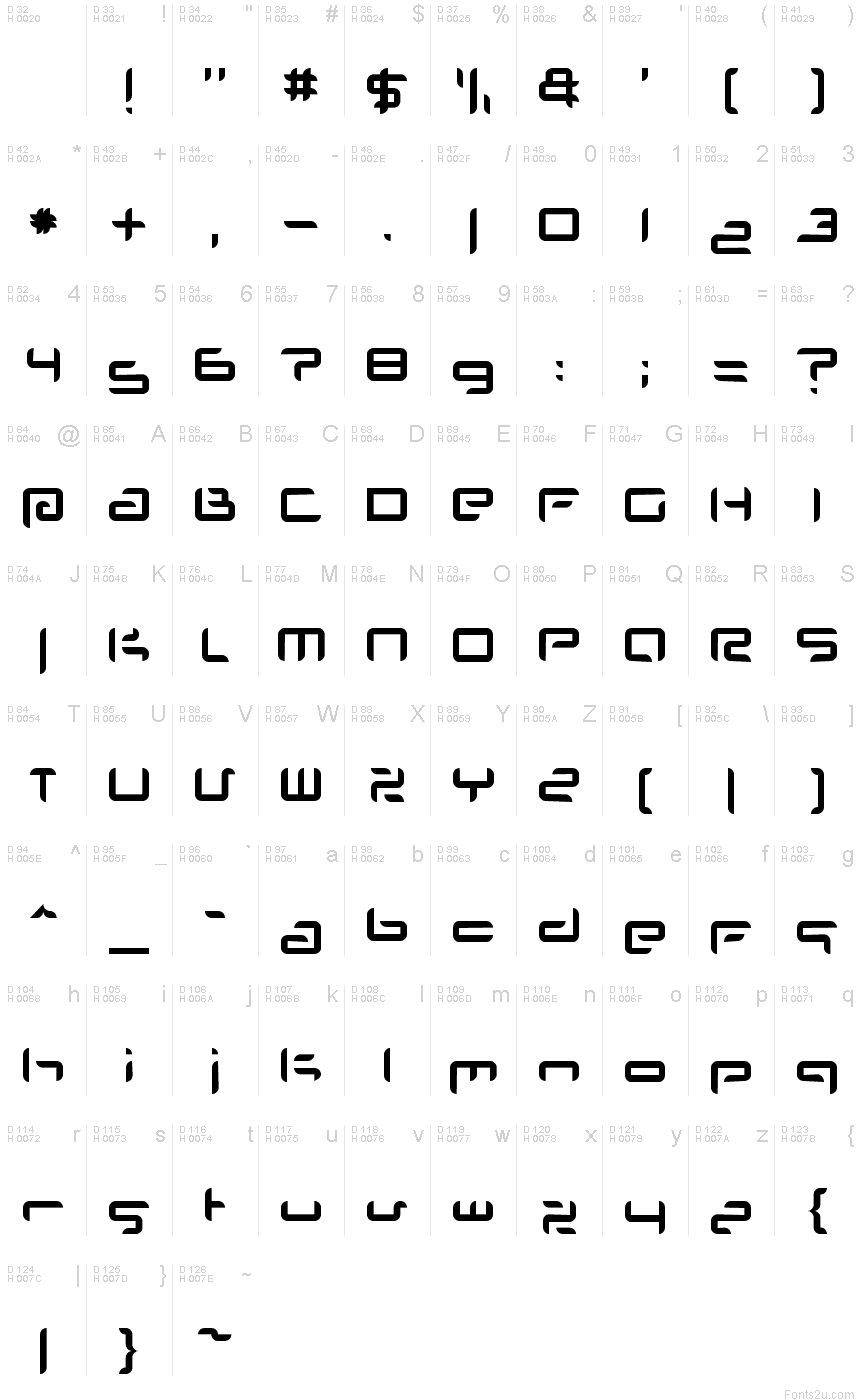
Planet Space di A Planet Font è un font display futuristico gratuito che richiama le atmosfere techno della fine degli anni '90. Le lettere sono costruite con tratti spessi e squadrati, caratterizzati da angoli interni arrotondati che creano un ritmo modulare fluido; il risultato è digitale, compatto e vagamente spaziale, senza risultare freddo.
È perfetto per flyer di club, titoli di giochi, grafiche per musica elettronica, packaging sci-fi e header web dove bastano poche parole per definire lo stile. Essendo un font gratuito, Planet Space dà il meglio di sé in loghi, title card e piccoli elementi di branding, perché la ripetizione delle curve ad angolo retto conferisce anche a poche lettere un forte ritmo sintetico.